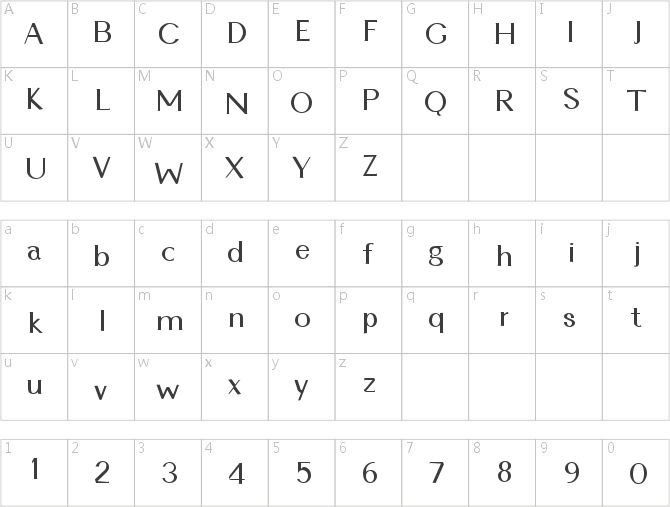
FZ BASIC 22 COND
FZ BASIC 22 COND介紹
FZ BASIC 22 COND字體字庫是一款讓人賞心悅目、百看不厭的英文字體,適合各類廣告和產品包裝設計應用,字體大小0.05MB,格式為ttf字體,上傳用戶是dqq520,作者/版權方為未知
FZ BASIC 22 COND效果圖